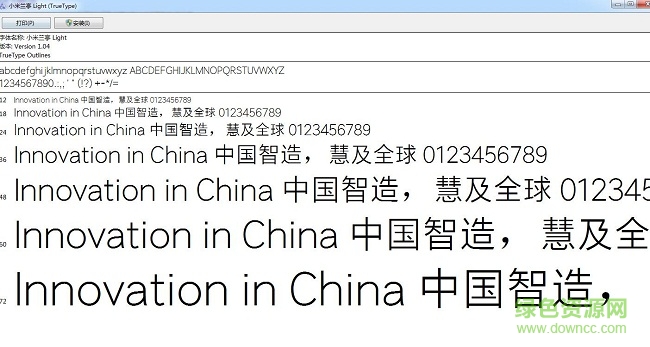
小米蘭亭細字體是一款ttf格式的無襯線免費字體,筆畫纖細,清晰度較高,辨識度強,具有一種現(xiàn)代機械圖形美感,可以用于海報設(shè)計,歡迎大家免費下載!
與漢字字體中的黑體相對應(yīng)。與襯線字體相反,該類字體通常是機械的和統(tǒng)一線條的,它們往往擁有相同的曲率,筆直的線條,銳利的轉(zhuǎn)角。